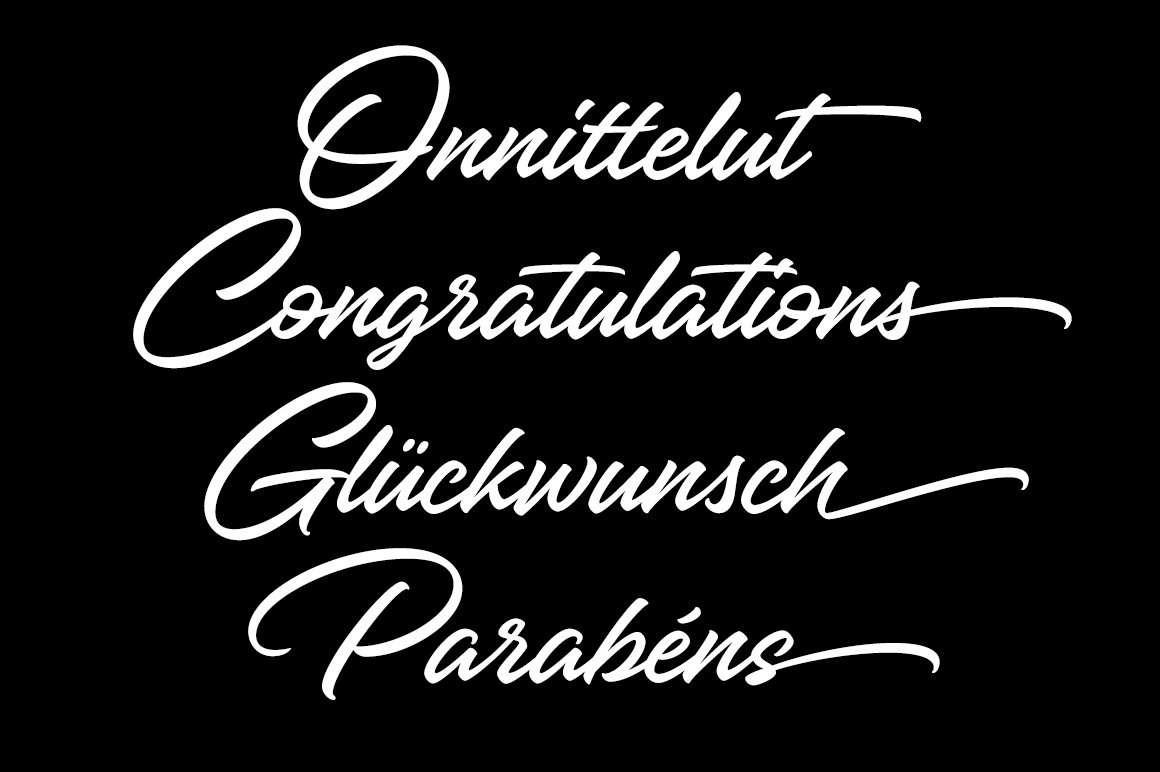
Tải font MTD Hangbird mở ra cho các nhà thiết kế và kiến trúc sư một lựa chọn phông chữ Brush Script cổ điển đầy đặn, lấy cảm hứng từ nghệ thuật vẽ bảng hiệu và bao bì thực phẩm của thập niên 1950. Với các đường nét viết thảo dày dặn, nhịp điệu nhún nhảy ấm áp và các góc lượn tự nhiên, MTD Hangbird việt hóa là chất liệu trực quan tuyệt vời để tạo nên điểm nhấn cho các bản vẽ phối cảnh tiệm bánh ngọt container, quán cà phê ven hồ hay biển chỉ dẫn homestay phong cách đồng quê.
Đường lượn phóng khoáng và nhịp điệu rực rỡ của font MTD Hangbird
Điểm cuốn hút của font việt hóa MTD Hangbird nằm ở sự kết hợp giữa nét bút lông mềm mại và độ dày nét đậm đà, mang lại độ phủ bề mặt lớn cùng khả năng nhận diện xuất sắc từ cự ly xa. Mỗi chữ cái đều sở hữu những đường liên kết mượt mà và nét cong tròn đầy sức sống, gợi nhớ đến tinh thần lạc quan, hiếu khách của các không gian ẩm thực truyền thống.
Sự ổn định về mặt cảm xúc của dòng font này giúp lan tỏa cảm giác gần gũi, ấm áp và kích thích vị giác của người xem. Khi kết hợp cùng các vật liệu kiến trúc mộc mạc như tường tôn sóng container sơn màu vàng kem, vách gỗ thông mộc hay đèn thả ánh sáng vàng ấm trong các căn nhà lắp ghép, Hangbird tạo nên sự hòa quyện thẩm mỹ sinh động.
| Phân loại phong cách | Retro Brush Script / Cursive / Packaging Display |
| Mục đích phù hợp | Biển tên tiệm bánh, menu cafe, logo ki-ốt ẩm thực |
Tư vấn từ chuyên viên: MTD Hangbird sở hữu nét chữ thảo đậm đà và độ uốn lượn phong phú. Để bản thiết kế đạt hiệu quả thẩm mỹ tốt, bạn chỉ nên sử dụng phông chữ này cho các tiêu đề chính, slogan ngắn hoặc tên món ăn đặc trưng. Phần nội dung mô tả kỹ thuật chi tiết nên đi kèm một phông chữ không chân thanh mảnh hơn để người xem tiếp nhận thông tin dễ dàng.
03 Ứng dụng phông chữ MTD Hangbird vào công trình thực tế
Nhờ vẻ ngoài tươi vui và tính gợi hình mạnh mẽ, bộ phông chữ này mang lại giá trị thực tế lớn trong khâu tạo điểm nhấn cho các công trình hiện đại:
- Biển hiệu mặt tiền cho Tiệm bánh và Quán Cafe Container: Những khối chữ uốn lượn đậm nét của Hangbird rất ăn ý khi gia công chữ nổi mica gắn viền kim loại trên vách tôn sóng, tạo nên diện mạo ngọt ngào và thu hút khách hàng ghé thăm chụp ảnh kỷ niệm.
- Hệ thống bảng thực đơn và quầy phục vụ: Phông chữ này khi in trên các bảng gỗ treo hoặc decal dán kính sẽ giúp các đề mục đồ uống chính trở nên bắt mắt, tạo cảm giác hấp dẫn và kích thích vị giác của thực khách.
- Trang trí không gian bếp ăn Homestay nghỉ dưỡng: Bạn có thể dùng phông chữ này để làm tranh trích dẫn phong cách sống, biển chào mừng tại khu vực ăn uống ngoài trời của căn nhà lắp ghép, mang đến bầu không khí ấm cúng cho du khách.
03 Lưu ý bố cục font Việt hóa MTD Hangbird luôn uyển chuyển và rõ ràng
Để khai thác hiệu quả vẻ đẹp của dòng font chữ thảo retro này mà không gây cảm giác bí bách cho bản vẽ, người thiết kế nên lưu tâm một số kinh nghiệm sau:
- Tránh viết hoa toàn bộ ký tự: Các ký tự hoa của Hangbird có độ uốn lượn và nét móc cầu kỳ. Việc viết hoa liên tiếp nhiều chữ cái sẽ làm các nét xoắn va chạm nhau, gây mất trật tự bố cục và làm câu văn trở nên khó đọc.
- Kiểm soát khoảng cách dòng: Do một số nét chữ có phần đuôi vươn xuống dưới hoặc dấu thanh vươn lên cao, bạn nên thiết lập khoảng cách dòng thoáng đãng để các ký tự không bị chạm nhau, giữ được tính liên tục của câu chữ.
- Kết hợp cùng gam màu cổ điển ấm áp: Hangbird phát huy hiệu quả thị giác cao khi phối cùng các tông màu mang sắc thái retro như đỏ thắm, vàng mù tạt, nâu cà phê hoặc kem sữa, giúp đường nét duyên dáng của bộ chữ được tôn vinh rõ ràng.